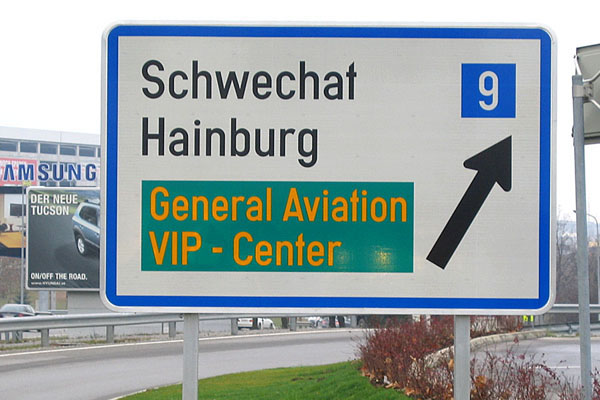
Schrift der Verkehrsschilder in Oesterreich?
die schweizer verwenden ja die SNV.
"die schweiz" verwendet zum glück seit ca. 3 jahren für alle neuen strassenschilder die "ASTRA Frutiger", eine leicht überarbeitete frutiger. soweit ich weiss mit relativ wenigen änderungen, vorallem anpassungen, um sie einfach auf die schilder zu kriegen. da bin ich mir aber auch nicht mehr sicher.
wusste nicht, dass die oesterreicher eine "eigene" DIN haben
und find sie auch nicht sonderlich schoen oder gar besser lesbar
als die normale DIN-schrift.
die schweizer sind da mal wieder einen schritt weiter ...